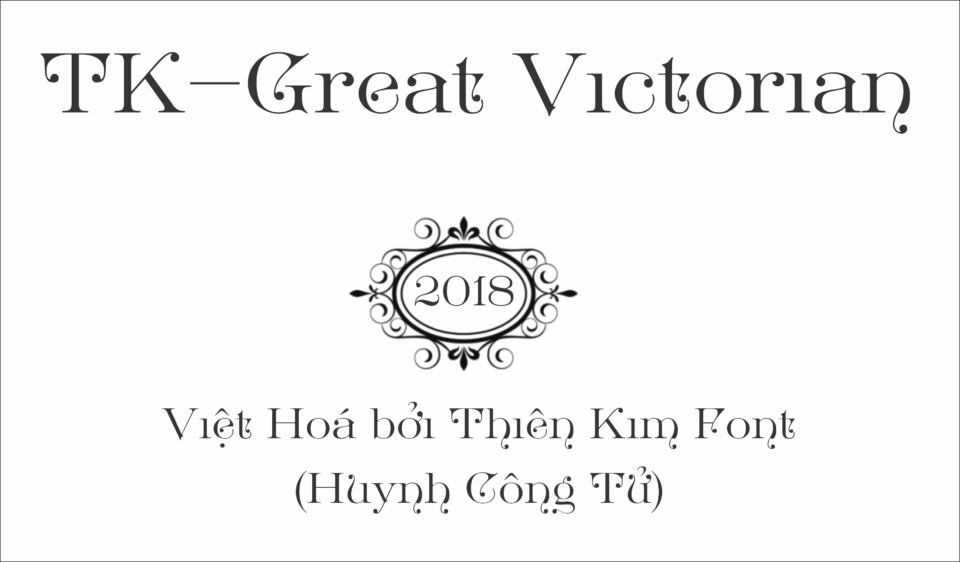
Font Việt Hoá TK-Great Victorian
Nếu bạn đang tìm kiếm một Font Miễn Phí mang đậm hơi thở nghệ thuật của thế kỷ 19, thì Font Việt Hoá TK-Great Victorian chính là sự lựa chọn hoàn hảo. Đây là bộ phông chữ lấy cảm hứng từ phong cách Victoria truyền thống, kết hợp giữa sự thanh lịch và vẻ đẹp cổ điển tinh xảo. Phiên bản này đã được tối ưu hóa tiếng Việt, giúp người dùng dễ dàng ứng dụng vào các thiết kế mà không lo lỗi hiển thị. Với các đường nét uốn lượn đặc trưng, bộ chữ này tạo nên một dấu ấn thị giác mạnh mẽ cho mọi dự án đồ họa.
Đặc điểm nổi bật của Font Việt Hoá TK-Great Victorian
Thiết kế tinh tế và nghệ thuật
Font Việt Hoá TK-Great Victorian sở hữu cấu trúc chữ độc đáo với những chi tiết trang trí phức tạp nhưng vẫn giữ được sự cân đối. Mỗi ký tự đều được chăm chút kỹ lưỡng, mang lại cảm giác hoài cổ và quý tộc. Điểm cộng lớn nhất là khả năng hiển thị sắc nét trên cả bản in và thiết kế kỹ thuật số, phù hợp cho nhiều mục đích sử dụng khác nhau của học sinh và nhà thiết kế.
Tính ứng dụng linh hoạt trong đời sống
Nhờ vẻ ngoài sang trọng, phông chữ này thường được sử dụng trong việc thiết kế bìa sách, thiệp mời, logo hoặc các ấn phẩm quảng cáo mang phong cách Retro. Đối với các bạn học sinh, bộ chữ này sẽ làm cho các bài thuyết trình hoặc dự án học tập trở nên sinh động và chuyên nghiệp hơn bao giờ hết. Bạn có thể kết hợp nó với các màu sắc trầm để tôn vinh vẻ đẹp cổ điển.